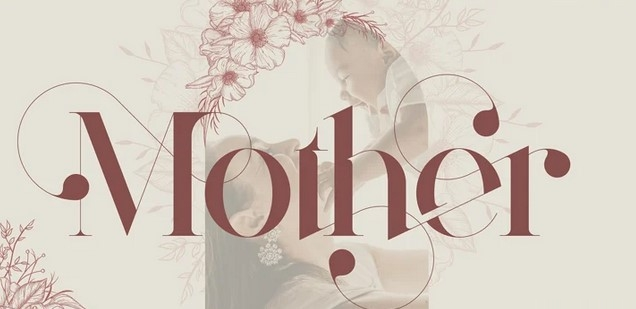
[Myfonts] Mother VP Font (2021)
Название: Mother VP Font (2021)
Представляем шрифт Mother Serif Typeface - 5 шрифтов
Mother назван в честь всех мам и детей, оставшихся позади.
Это женственный, хрупкий шрифт, состоящий из 5 шрифтов с глифами, альтернативами и многоязычной поддержкой, чтобы очаровать ваш следующий проект. Очень универсальный шрифт, который отлично работает в больших и малых размерах.